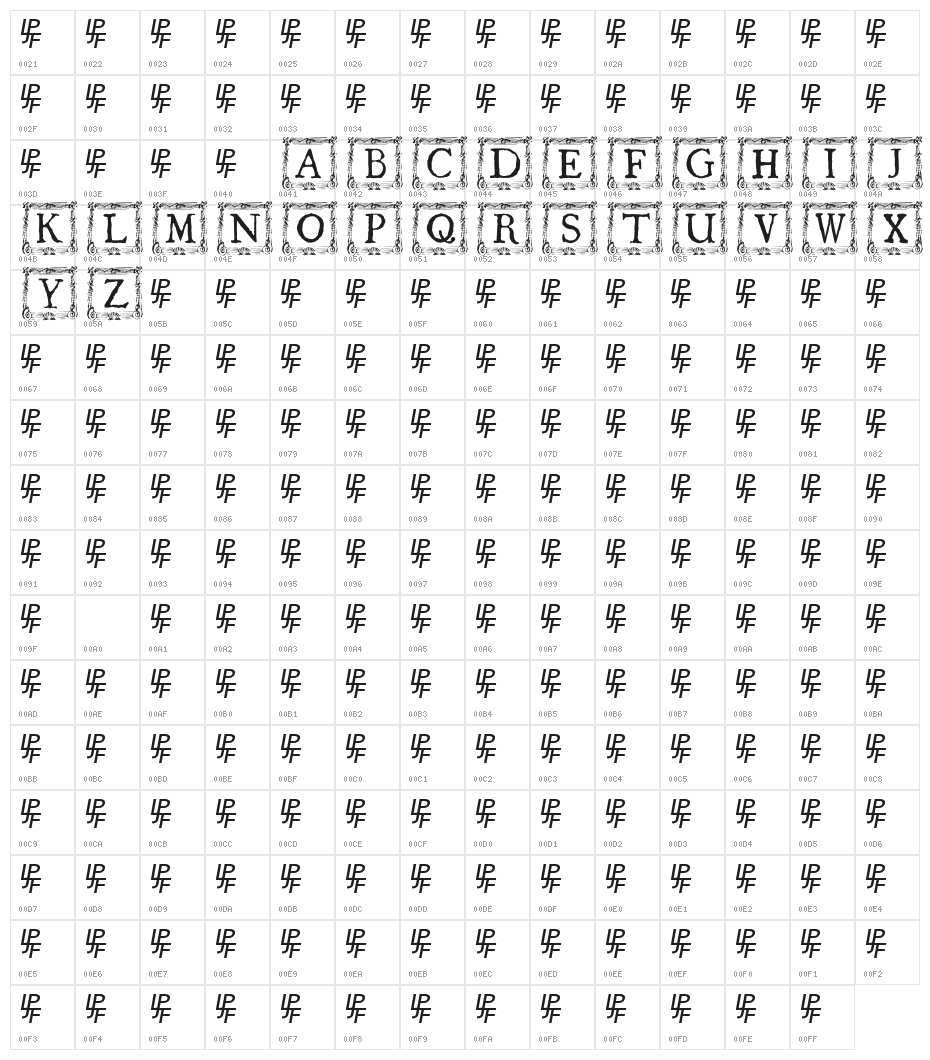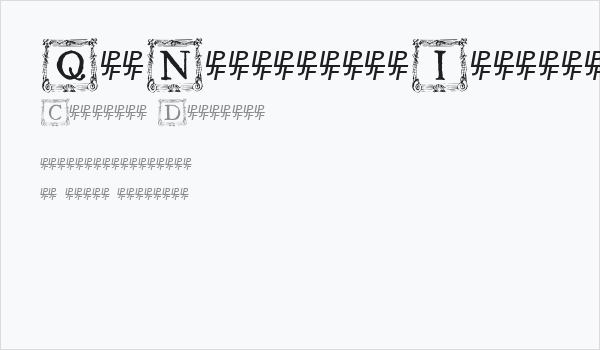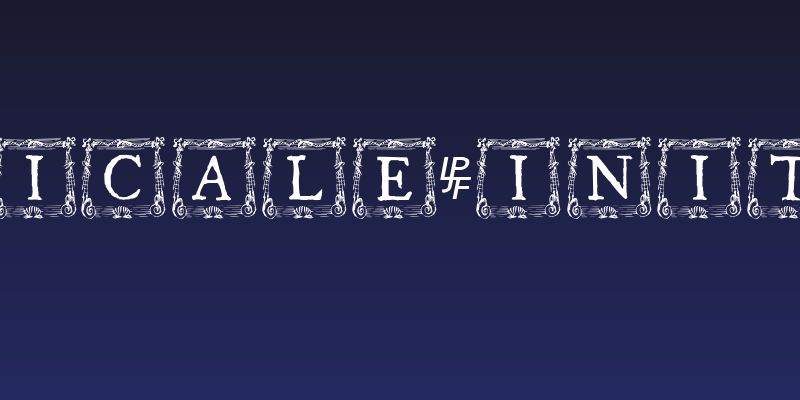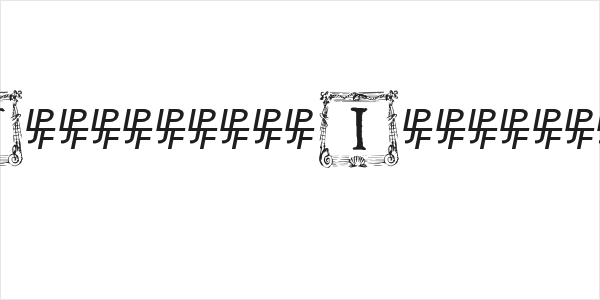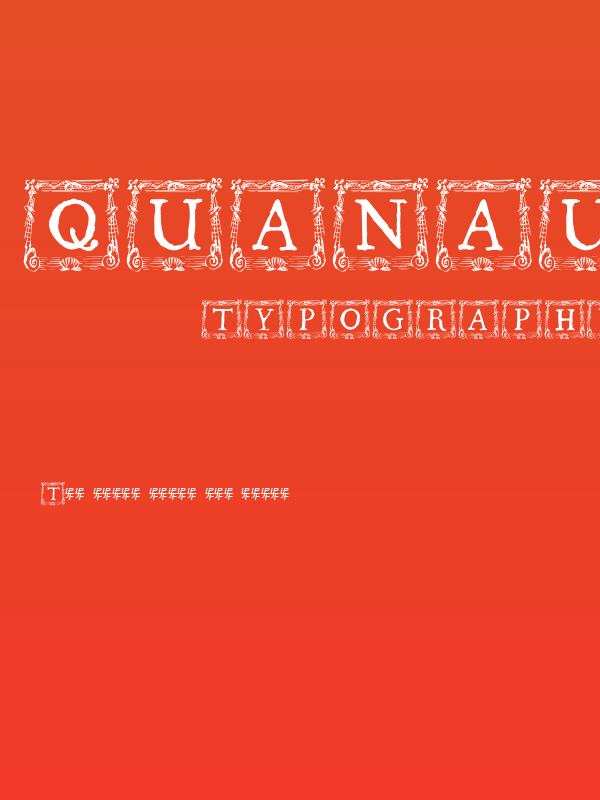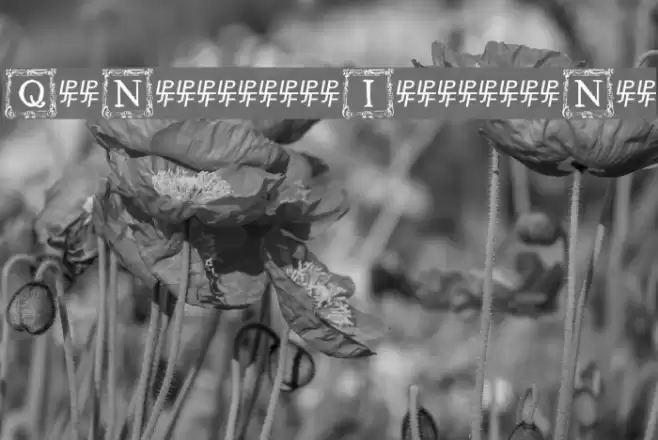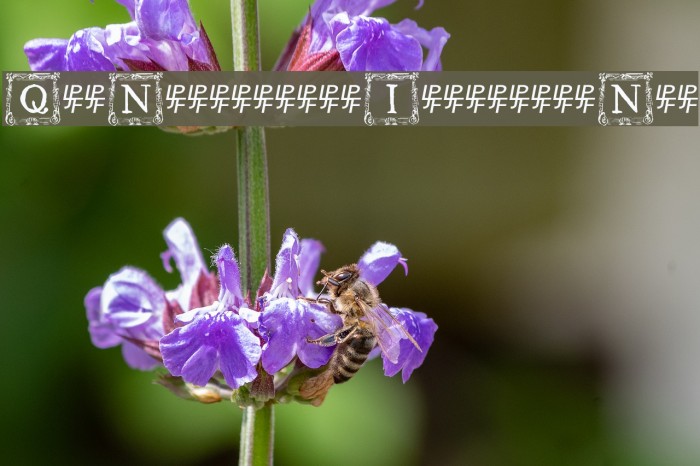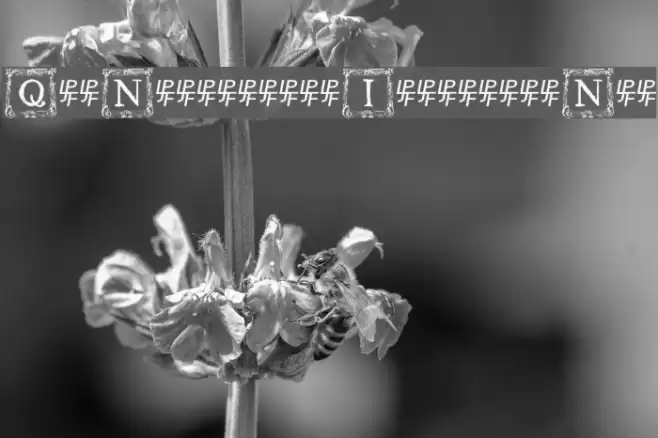
QuaNauticale_Initials_No3 Font
Fonts by Paul Lloyd
このフォントには 31 文字が含まれています。文字をクリックして詳細を表示。
| 用途 | Headlines, Logos, Invitations |
| おすすめプロジェクト | Perfect for wedding invitations, certificates, branding for luxury products, and any project needing a classic, elegant touch. |